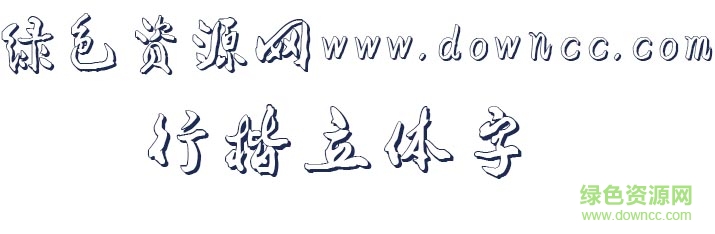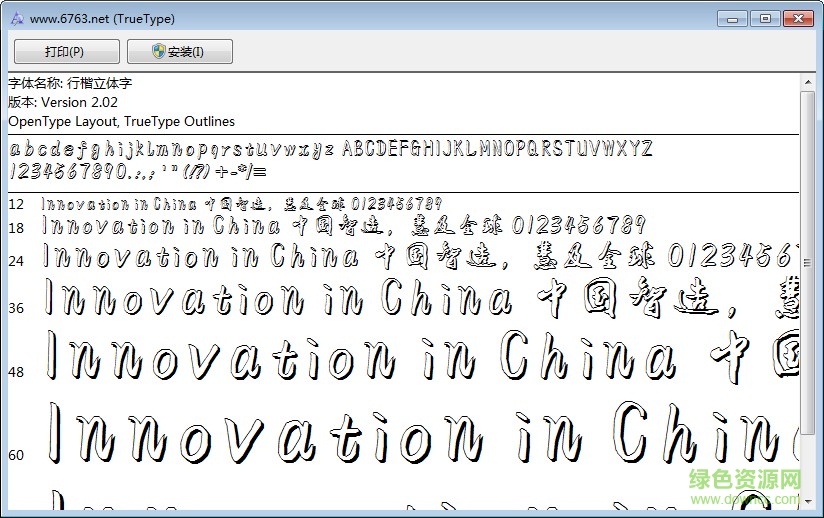
软件介绍 软件标签: 立体字 字体 行楷立体字是一款极具特色的空心立体字体,空心字体给人非常具有立体感,深受广大书法家和年轻人的喜爱,还有更多好看字体尽情期待,欢迎到绿色资源网下载体验!行楷立体简介:行楷立体字是一款非常有特色的行楷书字体,这款字体行云流水,字体潇洒,帅气张扬,空心字体给人非常具有立体感,非常适用于艺术设计、广告设计等领域。行楷立体字安装说明:方法一:控制面板/字体/文件/安装新字体;方法二:直接将字体复制到C:\WINDOWS\Fonts。方法三:针对win7系统,用户只需选中字体右键安装即可。注意事项:本站所有字体资源仅供个人学习与参考,如需商业使用请到相关官网授权。 软件截图 上一张下一张(1 / 1) 安装详细截图 猜你喜欢 行楷字体 行楷字体 行楷字体大全是绿色资源网小编为大家打包整理的行楷字体ttf合集,包含了几十款应用极广的行楷体,适用于影视、广告、平面、印刷各种行业领域,选择多样,下载便捷! 查看更多>> 汉仪苏泽立行楷精修版简 3.01M/中文/4.0/免费版下载 汉仪许静行楷字体 2.44M/中文/4.4/下载 繁体行楷字体大全 46.87M/中文/2.5/下载 经典行楷简体 常规 5.54M/中文/2.3/下载 文星简行楷 3.41M/中文/6.6/下载 stxingkai 3.41M/中文/6.3/免费版下载 其他版本下载 标题 大小 更新日期 下载 下载地址 电脑版 行楷立体字体 点击报错 软件无法下载或下载后无法使用,请点击报错,谢谢! 关闭报错反馈 请描述您所遇到的错误,我们将尽快予以修正,谢谢! *必填项,请输入内容 本类最新 dreamweaver字体库 首尔南山体字体 v1.06 官方版 潮字社风云简ttf 潮字社凌渡鲲鹏简体字体 潮字社曾玉波手书简字体 微博慧心字体 相关文章 Photoshop字体安装使用方法和技巧 如何解决“无法新增字体”问题 Win 7系统安装字体方法 网页字体大小设置方法 怎么改网页字体大小 在Linux系统中安装字体的几种方法 windows7字体显示问题:打开某些程序的时候显示的是乱码 用户评论 热门评论 最新评论 发表评论 查看所有评论(0) 昵称: 请不要评论无意义或脏话,我们所有评论会有人工审核. 字数: 0/500 (您的评论需要经过审核才能显示)